今回は
自分の手書き文字をなぞってみた
というお話をしたいと思います。
1 自分の手書き文字をなぞる経験
みなさんは
自分の手書き文字を
なぞったことはありますか。
書道を習っている人は
多かれ少なかれ
なぞったことがあるでしょう。
でも、ほとんどの人は
自分の字を
なぞっていないでしょう。
私の場合は
記憶が定かでは無いのですが
たしか
小学校で習字を習ったときに
なぞったことがあるはずです。
それ以外は記憶にありません。
そんな状態の私ですが
特に脈絡もなく
「他人様の字をなぞっておきながら
自分の字だけ隠すのは
おかしい。」
と思い始めました。
そこで
まず自分の手書き文字を
公開することにしました。
自分の手書き文字を公開しつつ、
文字をなぞる意味
について少し考えてみます。
その後に
自分の手書き文字をなぞってみたので
その感想をお伝えしたいと思います。
2 お題公開
今回
自分の手書き文字のお題を
2つ公開します。
私は普段自分が考えたことを
メモにして
ネタ帳のようにしています。
今回公開するのは
そのメモのうち2つです。
普通のメモの字は汚いのですが、
ネタ帳に残す字は
丁寧に書いています。
汚い字の方はまだ勇気が要るので
丁寧な方だけを
公開することにしました。
一応自分向けの字です。
それでは、まず1つ目。
お題1
この章で言いたいことは
このお題1に書いてあります。
なぞり書きには多くの意味がある。
・見ながら書く臨書との違い
・・・より肉薄
・なぞり方の違いで感想も異なる。
・内容を読みながらなぞる。
・とにかく線を写すつもりでなぞる。
・自分の字をなぞるときの特殊性
・そもそもその自分の字は、
自分向け?他人向け?
・字を見ずになぞる
・じっくりなぞる
どうでしょうか。
活字が出てくると、
手書き文字をすっ飛ばして
活字を読みたくなりませんか?
活字の威力をまざまざと感じます。
それはさておき、
一応このとおりお話をします。
まずは、お題1を使って、
手書き文字をなぞる意味
のお話をしたいと思います。
3 手書き文字をなぞる意味
これからお話しする内容です。
再掲します。
お題1
なぞり書きには多くの意味がある。
・見ながら書く臨書との違い
・・・より肉薄
・なぞり方の違いで感想も異なる。
・内容を読みながらなぞる。
・とにかく線を写すつもりでなぞる。
・自分の字をなぞるときの特殊性
・そもそもその自分の字は、
自分向け?他人向け?
・字を見ずになぞる
・じっくりなぞる
3-1 見ながら書く・なぞって書く
書道を習っている人は、
他人の字をよく見て
それをお手本にしつつ、
手元で自分の字を書く練習を
されているようです。
これを
「臨書」というそうです。
人によっては、
なぞる時も「臨書」と呼ぶそうです。
見ながら書くときと
なぞり書きのとき。
何が違うでしょうか。
私の経験では、
なぞり書きの方が、
他人の手書き文字の線を
よく見ている感覚があります。
そして、
他人の手書き文字から
その人の個性を感じ取っています。
要するに
見ながら書くよりも
なぞり書きの方が
お手本の人に肉薄している
感じがあります。
人と話す場合にたとえてみます。
見ながら書く =
テーブルの向こうに座っている
相手の人と会話をするイメージ
です。
なぞって書く =
なれなれしく
相手の人の身体に触れながら
話すイメージ
です。
見ながら書くのと
なぞって書くのでは、
これぐらいの
「肉薄」度の違い
を感じます。
3-2 なぞり方の違いで感じ方も異なる
見て書くときよりも
なぞって書くときは、
より肉薄度が強いです。
ですが、
同じなぞり書きの中でも
なぞり方(意識)が違うと
感じ方がさらに異なってきます。
たとえば
書いてある文字を読みながらなぞると
自分が文章の内容に入り込んでいく
という感覚になります。
このときは
頭の中に、文章の内容の情景が
浮かび上がります。
これをうまく形容する用語は
思い浮かびません。
これに対し
手書き文字の書きぶりを見ることに
重点をおいて
なぞる方法もあります。
そのときは主に
文字の形がどうなっているかという点に
目が行きます。
このようななぞり方を
文字の形の臨書、すなわち
「形臨」(けいりん)
というそうです。
さらに
なぞる目的が変わり、
文字を書いた人に興味をもって
「どうして
こんな風に書いたのだろう」と
考えながら
なぞる場合もありえます。
このときは
手書き文字を書いた人の
筆遣いの意味をとおして
気持ちや性格が見えてくる感じ
があります。
このような場合を
意味の臨書、すなわち
「意臨」(いりん)
というそうです。
文字で表現された情景が浮かんだり、
文字の形が目についたり、
書いた人の気持ちや性格が見える。
同じ手書き文字をなぞっているのに、
何を学ぼうとしているのかによって
感じ方が変わってくる。
まるで鏡みたいです。
何人かが同時に同じ鏡を見ても
見る人の位置によって違う風景が映る。
そんな現象に似ています。
私にはとても不思議な現象に思えます。
みなさんはどう感じられますか。
文字なぞりは不思議な感じがしませんか。
3-3 自分の字をなぞるときの特殊性
私は今まで色々な他人の字を
なぞってきました。
ですが今回のように
自分の字をなぞるときは、
他人の字をなぞるときとは異なる
特殊性が出てきます。
明らかに違う点は
書き手が自分なので
書き手がどんな気持ちで書いたかが
自分にはわかっているという点です。
次に違う点は
他人の自分向けの手書き文字は
入手しにくいが、
自分の自分向けの手書き文字は
入手しやすい点です。
もう少し詳しく説明しましょう。
手書き文字は
自分向けの字の場合と
他人向けの字の場合があります。
日記やノートの場合など
自分向けの字であれば、
自分の内面の特徴が表れるでしょう。
他方
手紙の場合など
他人向けの字であれば、
他人の目を意識した
外面の特徴が表れると思います。
このように
自分の自分向けの手書き文字と
自分の他人向けの手書き文字は
特徴が違ってきます。
ここで
「いや他人の手書き文字だって
自分向けのときと
他人向けのときが
あるでしょう。」
という声が聞こえてきそうです。
なかなか鋭いツッコミです。
どう考えたら良いでしょうか。
たしかに
他人の手書き文字が
自分向けのときと
他人向けのときに分かれることは
まちがいありません。
ですが、
他人が自分向けに書いた手書き文字は
ふつうは公開されていません。
(例:他人の日記)
他人の自分向けの手書き文字は
入手しにくいといえます。
反対に
自分の自分向けの手書き文字は
今すぐにでも手元で書けます。
このように
他人の自分向けの手書き文字は
入手しにくく
自分の自分向けの手書き文字は
入手しやすい
という違いがあります。
それでは
自分向けの字と他人向けの字。
どちらの字が
性格が出やすいでしょうか。
やはり、
自分向けの字でしょう。
他人の目を意識しないので。
そういうわけで
地の性格が出やすいので、
今回は、
もじのすけの自分向けの字を
お題2として公開し、
なぞることにしました。
そして
自分の字をなぞるにあたっては、
じっくりなぞるやり方と
字に従わずになぞるやり方の
2つを試してみました。
なぞってみたら
それぞれのやり方で
発見がありました。
3-4 小さなまとめ
以上がお題1を使った
なぞり書きの意味のお話でした。
結論をまとめておきます。
①見て書くのとなぞって書くのでは
肉薄度に違いがある
②なぞって書くときでも
どんな目的でなぞるかによって
感想が異なる
③自分の自分向けの手書き文字は
他人の手書き文字と違って
入手しやすい
④自分向けの手書き文字は
地の性格が出やすい
The New Zealanders
Author:George French Angas (British, 1822–1886)
Date:1847
Culture:London: T. McLean, 1847
George French Angas | The New Zealanders | London: T. McLean, 1847 | The Met
4 自分の手書き文字をなぞってみた
それでは
お題2を公開します。
お題2をなぞりましたので、
こちらを見ていってください。
なぞる前はこちら。
あえて活字化はしません。
誤字も写真を撮ったときに
気づきました。
恥ずかしいですが
そのままにしています。
お題2(なぞる前)
最初の4行は、
丁寧に字を見ながらなぞりました。
「・速すぎると思考が止まる。」以下の
最後の2行は、
字をなぞろうとせずに
その字をもう一度書くような感覚で
素早くなぞりました。
なぞった後のメモがこちらです。
なぞった後に気になって
誤字を訂正しています。
お題2(なぞった後)
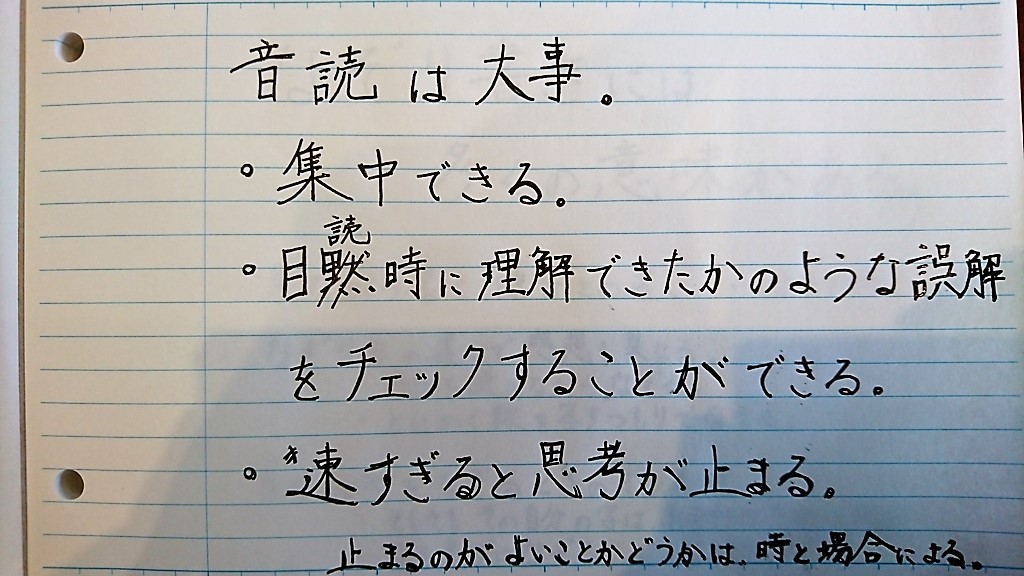
なぞってみていろいろと
感じるところがありました。
その感想は次回にまわしたいと思います。
読者のみなさんも
言われてみなければ
きっと
自分の手書き文字をなぞろうとは
思わないことでしょう。
もし興味が湧いたら、
ぜひ自分の手書き文字を
なぞってみてください。
きっと
今までにない変な感触
を感じると思いますよ。
(決してオススメしませんが)
もし、お題1、お題2の
手書き文字をなぞれば、
もじのすけの性格が
完全に見透かせるかもしれませんね。